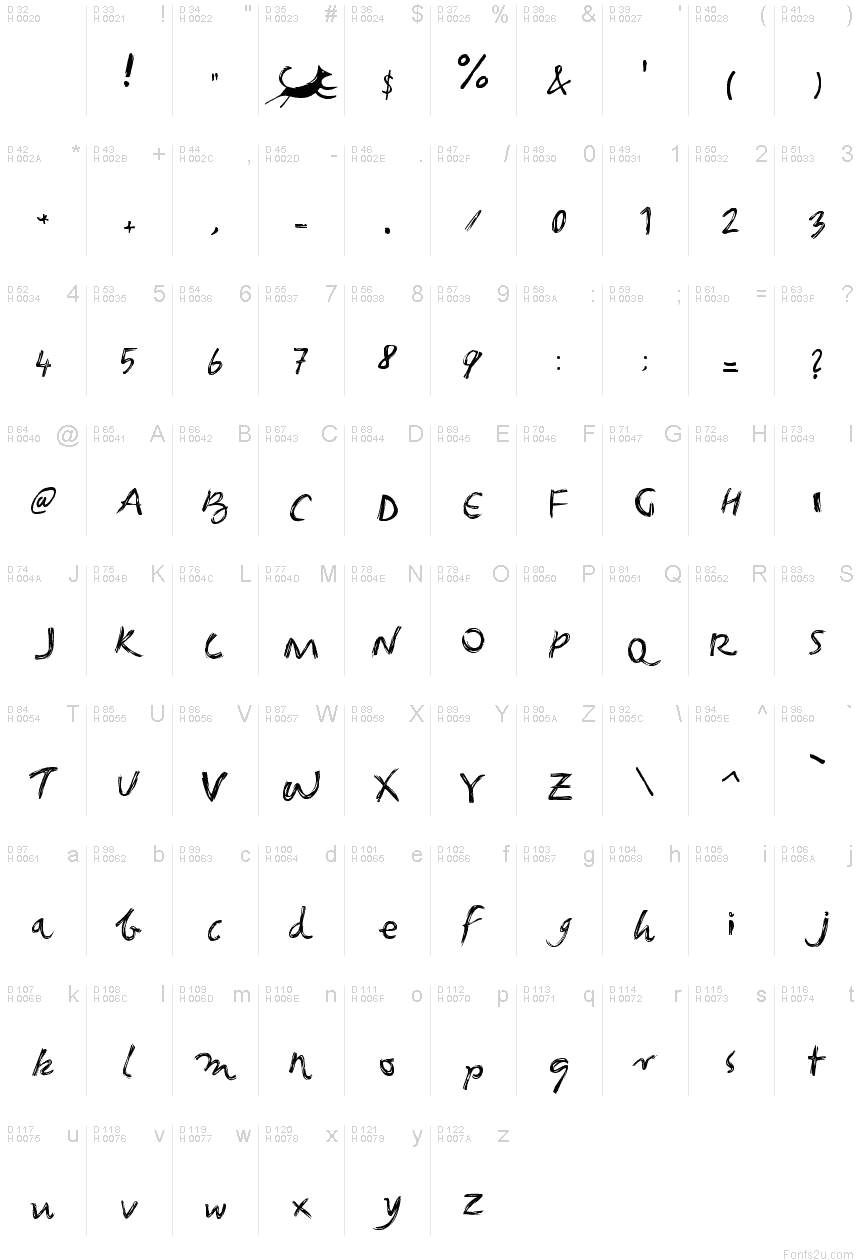
Foxgrunge di Phil Campbell è un font grunge gratuito che sembra graffiato sulla pagina con un pennarello spesso e inchiostrato. Tratti irregolari si scontrano con curve più fluide, conferendo a ogni parola un'energia selvaggia e calligrafica che risulta grezza e potente, tutt'altro che rifinita. I bordi irregolari, le sovrapposizioni e la texture graffiante gli conferiscono un aspetto genuinamente improvvisato, come note strappate da un taccuino o da una locandina di un concerto.
Con Foxgrunge, i tuoi titoli non si limitano a essere presenti: si fanno notare. Questo font gratuito è perfetto per locandine punk o rock, fanzine, branding per sport estremi, copertine horror, streetwear e grafiche per social media che richiedono un look DIY audace. Usalo in grande formato per il massimo impatto e abbina Foxgrunge a un font sans serif condensato e pulito per il corpo del testo, così da mantenere il caos sotto controllo.